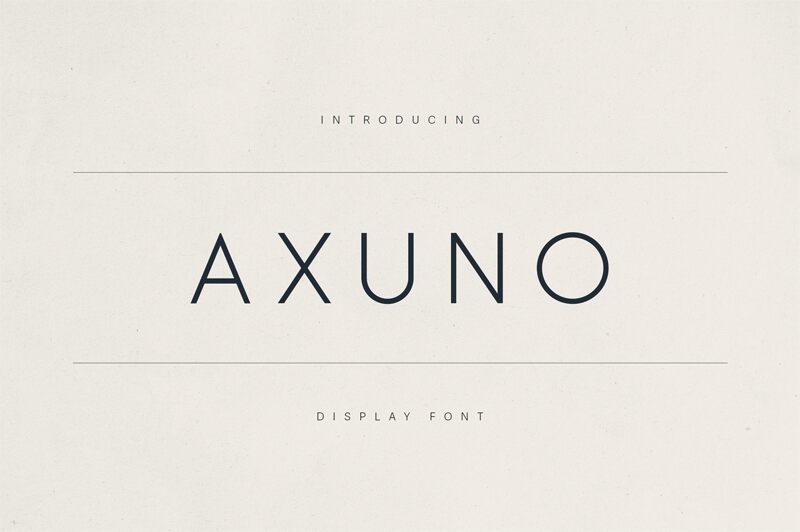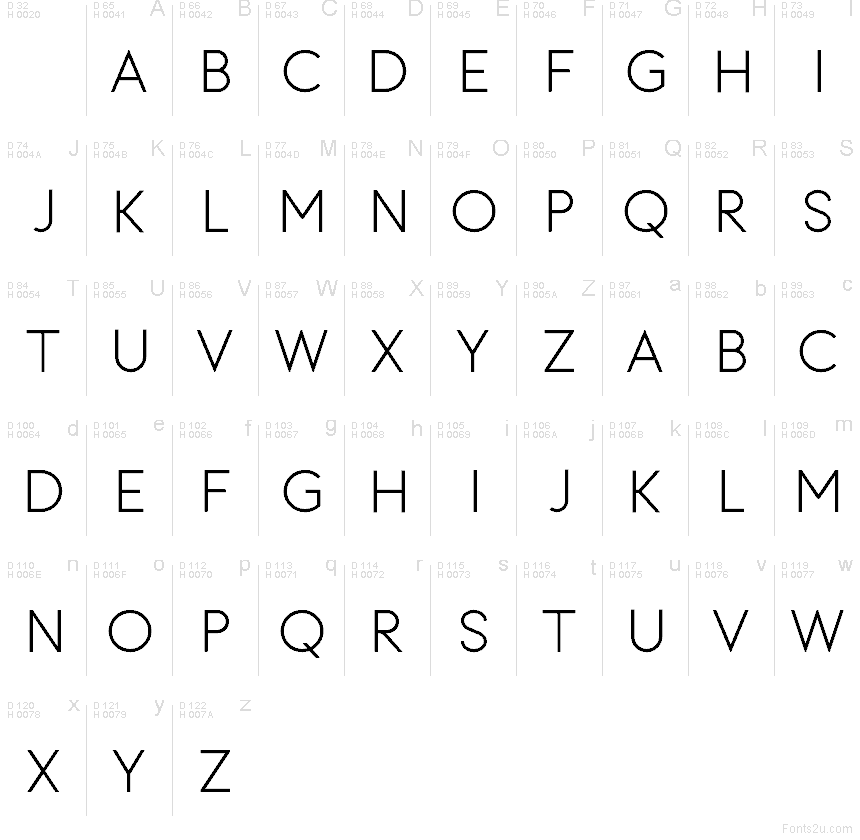
Axuno ist eine kostenlose geometrische serifenlose Schrift, die durch lange, gerade Striche und weit geschwungene Rundungen definiert ist – das verleiht dem Schriftbild einen reduzierten, architektonischen Charakter. Das nahezu kreisrunde O und die scharfen, dreieckigen Verbindungen bei Buchstaben wie A und X verleihen dem Design einen ruhigen, fast diagrammartigen Rhythmus, der sich deutlich von einer neutralen Grotesk abhebt.
Diese Ausgewogenheit eignet sich hervorragend für Technologie-Branding, Galerieplakate, Verpackungen, App-Begrüßungsbildschirme und kurze redaktionelle Überschriften, bei denen eine klare Geometrie die visuelle Wirkung trägt. Axuno eignet sich zudem ideal für Logos und Beschilderungen, insbesondere wenn Sie einen maßvollen, offenen Look suchen, der nicht zu kompakt oder zu mechanisch wirkt.